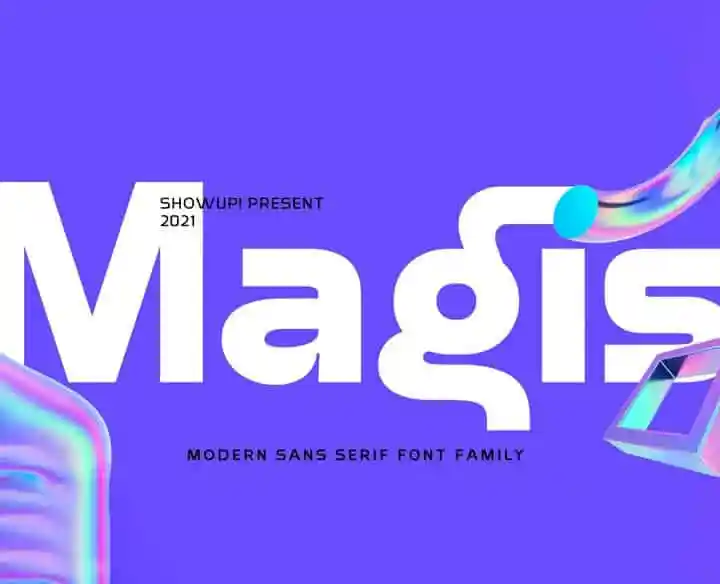
Magis - Sans Serif Font Demo
Magis Sans Serif é uma família de fontes sans-serif geométrica criada pelo designer Typefoundry Showup!. Esta fonte vem com 18 pesos diferentes, incluindo 9 uprights que combinam perfeitamente com seus tipos itálicos. Suas proporções elegantes e minimalistas são ideais para qualquer projeto moderno em design de interface de usuário, gráficos ou branding digital. Com seu formato variável, Magis® traz energia e flexibilidade ao seu layout, tornando-a uma opção perfeita para designers que buscam estilizar seus projetos de forma eficaz sem comprometer a legibilidade. Engajante e versátil, ela é uma ótima escolha para quem busca adicionar um toque moderno e inovador às suas criações digitais.